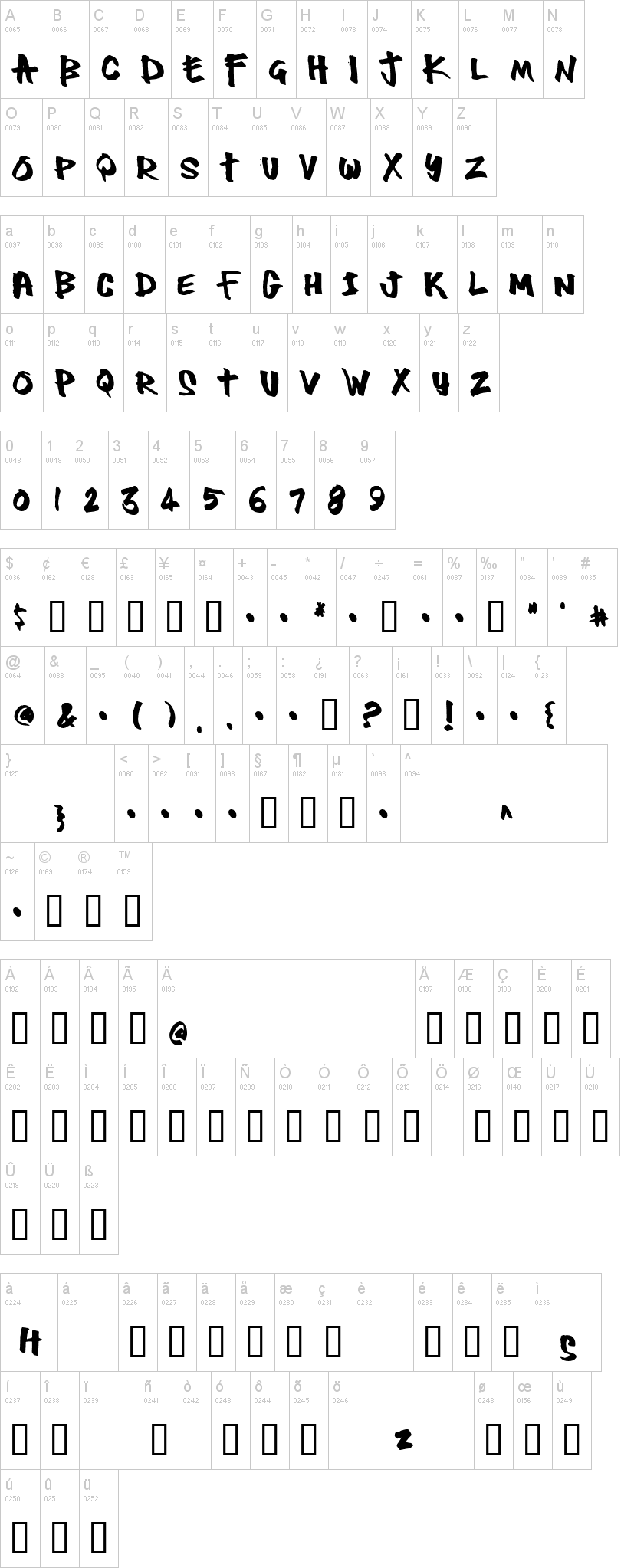
Thug字体是一款拉丁文字体,由著名设计师Daniel Hernández于2018年创作。它拥有独特的设计风格,可以提供更多的表达力,从而让文本具有更加强烈的个性。字体的粗细变化和曲线的弯曲让它具有更多的表现力,从而使文字更具生动性。此外,它还具有不同的字母形状,可以使文本更加有趣。Thug字体可以用于各种类型的印刷品,如海报、书籍、杂志、海报等,也可以用于网页设计。内容介绍
Thug是一款非常不错的手写艺术字体,具有很好的视觉感,适合于文化类的宣传设计、商业类品牌的广告和产品包装设计以及个性化文字排版等较多场景。